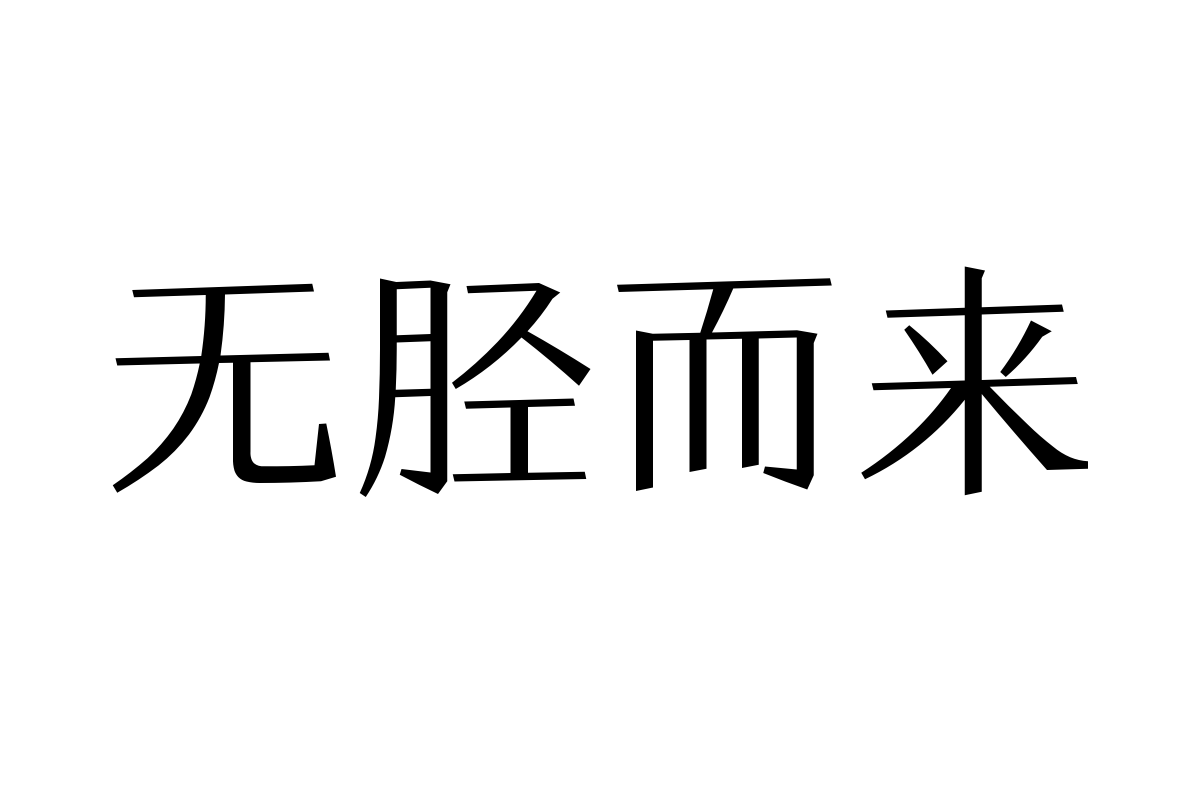
汉仪意宋简是一款现代简约风格的中文字体,具有独特的艺术风格和强烈的视觉冲击力。这款字体线条流畅,结构简洁,给人一种清新、自然的感觉。同时,它的笔画粗细变化丰富,既有粗犷的线条,又有细腻的勾勒,使得整体视觉效果更加饱满。
在设计上,汉仪意宋简注重细节的刻画,每个字的形态都经过精心设计,使得整体作品更加精致。无论是标题还是正文,都能够展现出独特的个性和魅力。
总之,汉仪意宋简是一款极具特色的中文字体,无论是在艺术表现上还是在实用性上,都能够为设计师提供丰富的灵感和选择。